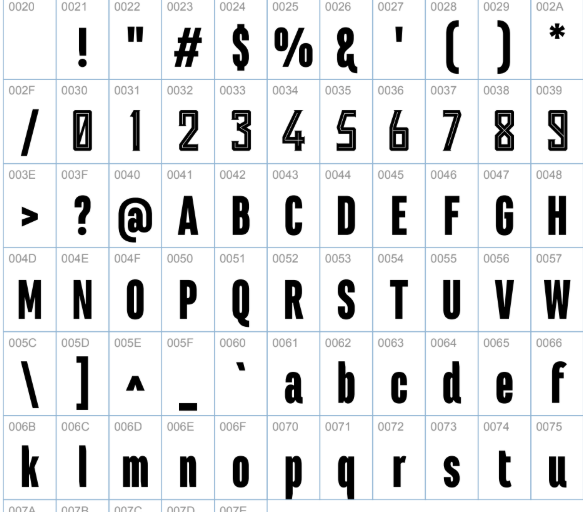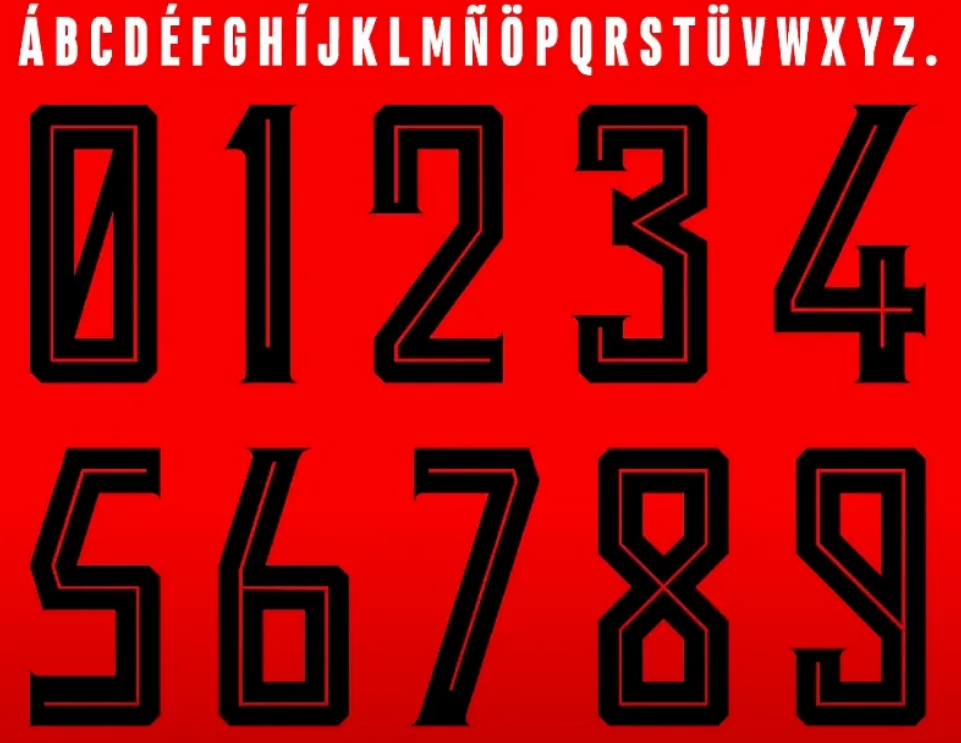
O retorno do Esporte Clube Vitória à elite do futebol brasileiro exige um uniforme à altura. A temporada 2024 marca não apenas a presença do Leão na Série A, mas também a consolidação da parceria com a fornecedora Volt Sport, que trouxe uma identidade visual moderna e impactante para o Barradão.
Estilo Visual da Fonte
A tipografia desenvolvida pela Volt Sport para o Vitória em 2024 reflete a agressividade e a energia do clube. Trata-se de uma fonte com peso “Bold”, garantindo excelente leitura à distância e presença marcante nas costas do uniforme.
O design apresenta cortes angulares nos terminais dos números e letras, conferindo uma sensação de velocidade e modernidade. Ela foi projetada para contrastar perfeitamente tanto sobre as listras verticais do manto titular quanto sobre o fundo limpo da camisa reserva, sendo essencial para reproduzir a autenticidade dos uniformes de jogo.